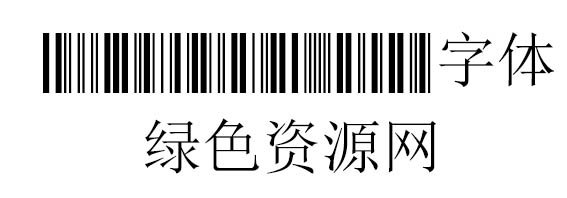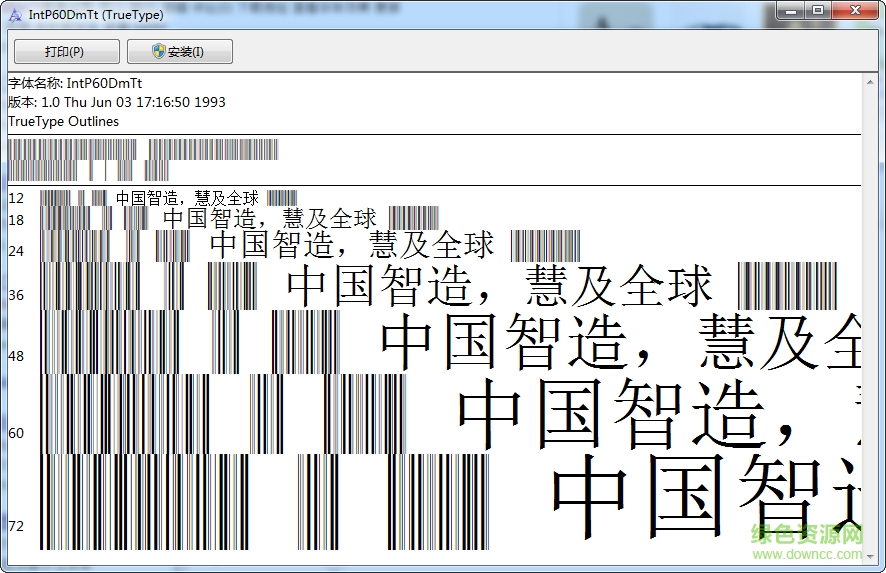
IntP60DmTt是一款條形碼字體,這款字體看起來(lái)比較精致,用起來(lái)更加方便,十分好看,實(shí)用性強(qiáng),相信不多說(shuō),老司機(jī)都知道,喜歡的用戶就來(lái)綠色資源網(wǎng)下載體驗(yàn)唄!
IntP60DmTt是一款非常好用的條形碼字體,他將文字以條形碼的形式呈現(xiàn)